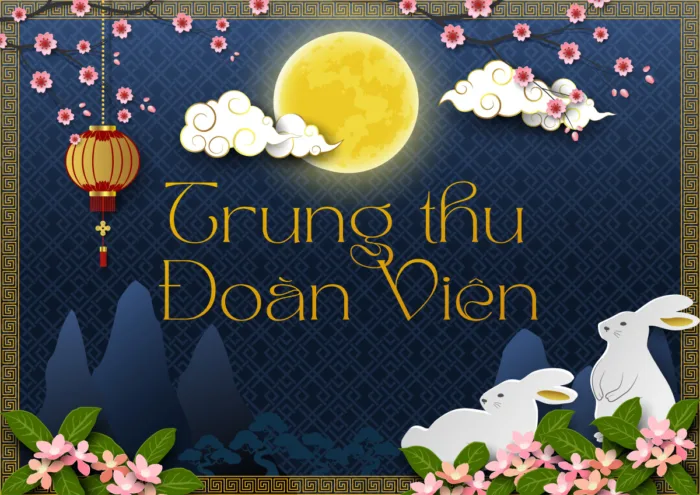
DVN Tan – Font chữ phong cách Á Đông phù hợp cho Trung Thu, Tết và lễ hội
DVN Tan là một kiểu chữ mang đậm hơi thở Á Đông, được thiết kế với đường nét thanh mảnh, mềm mại nhưng vẫn giữ được sự trang trọng. Font này đặc biệt phù hợp cho các dịp lễ hội truyền thống như Tết Trung Thu, Tết Nguyên Đán, lễ hội mùa xuân hay các sự kiện văn hóa châu Á.
Sự kết hợp giữa các đường cong uyển chuyển và nét cắt tinh tế tạo cảm giác vừa cổ điển vừa hiện đại, gợi nhớ đến phong cách trang trí trong nghệ thuật Á Đông. Font có thể sử dụng tốt cho poster, banner lễ hội, bao bì quà tặng, thiệp chúc mừng hay bất kỳ thiết kế nào cần gợi lên sự ấm áp và trang trọng của ngày Tết.